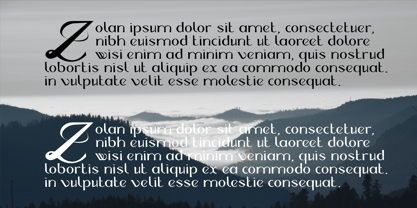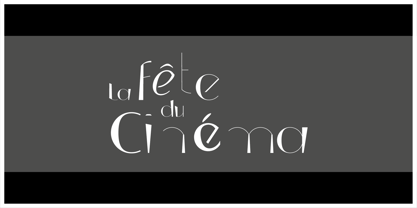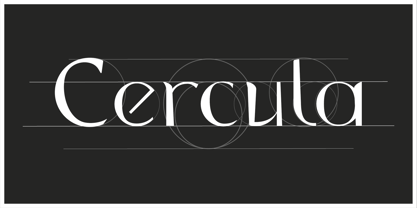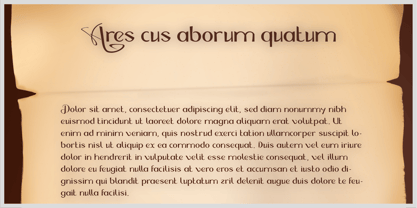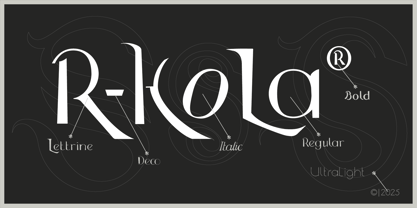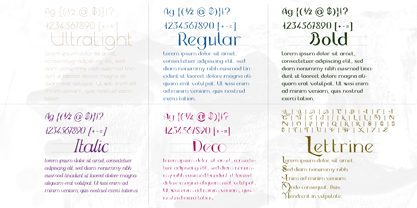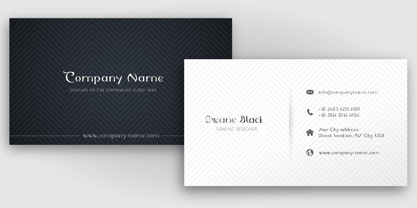
Cercula
The Cercula Font Family was designed by JC Mehring and published by JC Creation Design. Cercula contains 6 styles and family package options.
Cercula est une famille typographique fantaisiste, basée essentiellement sur des cercles. Elle se décline en cinq variantes et est complétée par une version "lettrine" (uniquement pour les lettres capitales). La version "Deco" est inspirée par le style "Art déco". cette typographie peut être utilisée pour du texte et toutes autres conceptions graphiques.